콘텐츠의 완성도를 높이는 폰트의 힘! 다양한 컨셉별 무료 영문 폰트 모음
콘텐츠 제작 시 가장 먼저, 그리고 가장 중요하게 생각하는 것이 하나 있습니다.
바로 한 번에 시선을 사로잡는 서체인데요콘텐츠 기획과 디자인에 잘 어울리는 서체는 콘텐츠의 완성도를 높여 줍니다. 저작권 때문에 고민이 많아 항상 무료 폰트를 찾아다니기 바빴던 디자이너와 기획자를 위해 컨셉 별로 사용할 수 있는 무료 영문 폰트를 소개해 드리겠습니다.
1. Relativescript –http://www.fontart.net/home.php
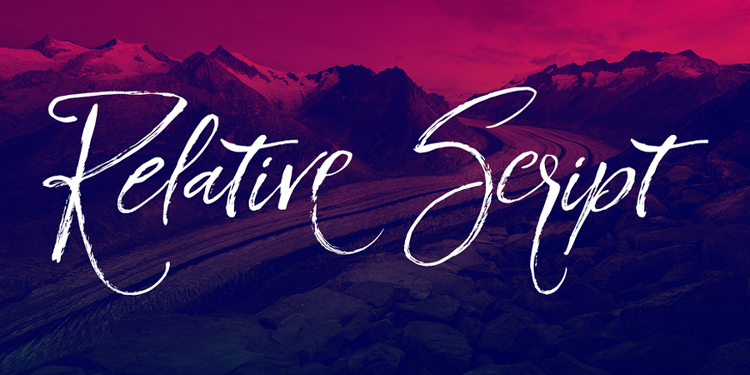
멋스러운 필기체입니다.
2. LAZER –https://www.graphicpear.com/lazer-free-font/
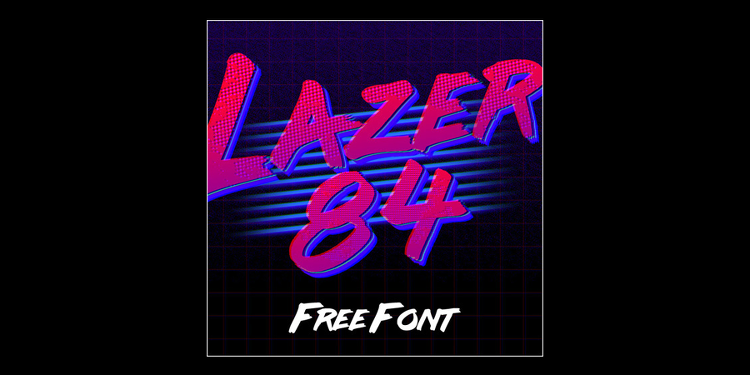
레트로 느낌의 서체입니다.
3. Bicycle –https://www.graphicpear.com/bicycle-free-font/
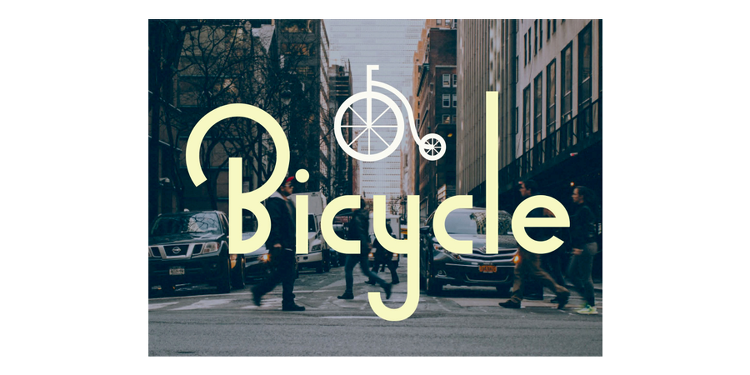
자전거에서 영감을 얻은 산세리프 서체입니다.
4. Ethelvina –https://www.graphicpear.com/ethelvina-free-gothic-typeface/
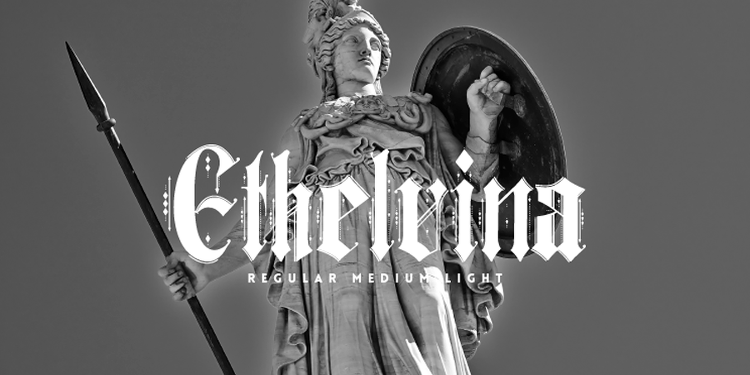
블랙레터 서체입니다.
5. Lorano ExtraLight – http://graphicburger.com/lorano-extralight-typeface/
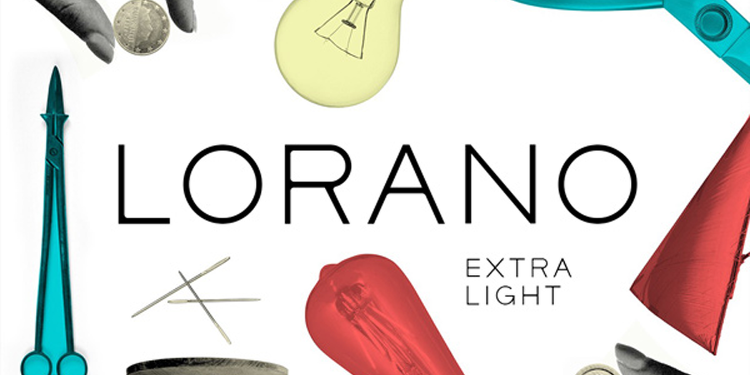
미니멀리즘에 어울리는 산세리프 서체입니다.
6. Humblle Rought – http://graphicburger.com/humblle-rought-free-font/
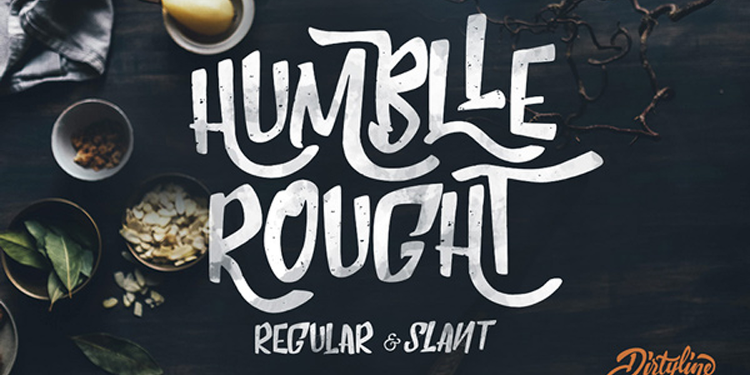
빈티지 서체입니다.
7. Fibon Sans http://graphicburger.com/fibon-sans-regular-weight-free/
가독성을 고려한 기하학적인 산세리프 서체입니다.
8. Butler –http://graphicburger.com/butler-free-typeface/
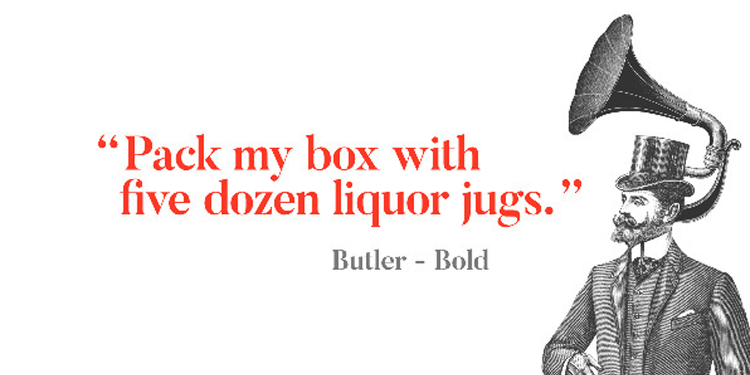
고급스러운 세리프 서체입니다.
9. COCO –https://dribbble.com/shots/759587-COCO-Free-Fashion-Typefamily
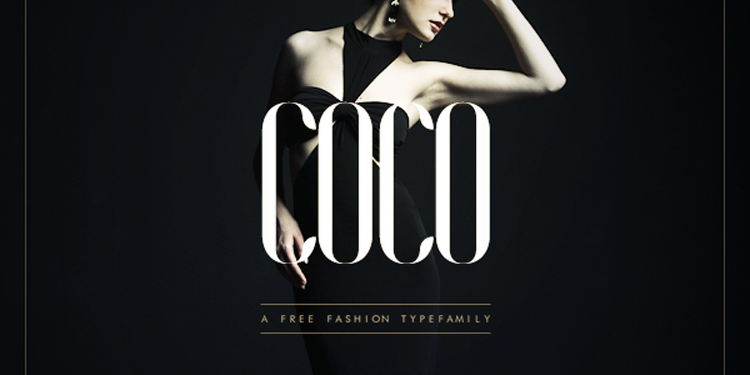
패션 잡지에서 볼 것 같은 세리프 서체입니다.